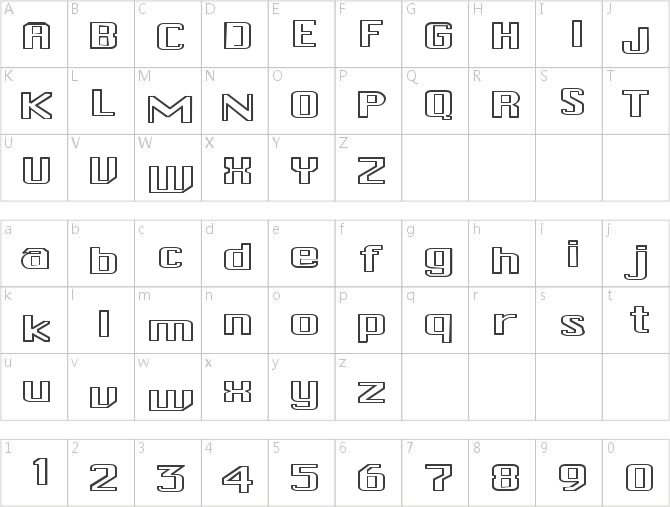
FZ BASIC 46 HOLLOW EX字體字庫(kù)是一款讓人賞心悅目、百看不厭的英文字體,適合各類(lèi)廣告和產(chǎn)品包裝設(shè)計(jì)應(yīng)用,字體大小0.08MB,格式為ttf字體,上傳用戶(hù)是 造物設(shè)計(jì)師,作者/版權(quán)方為未知